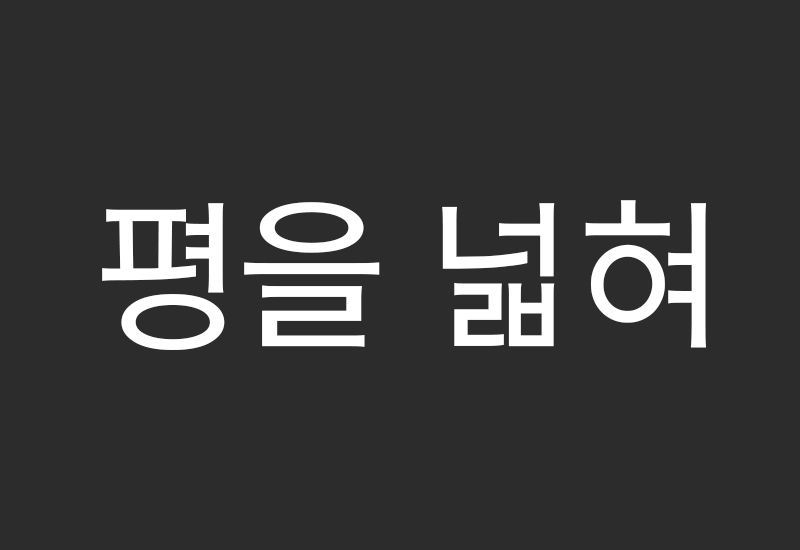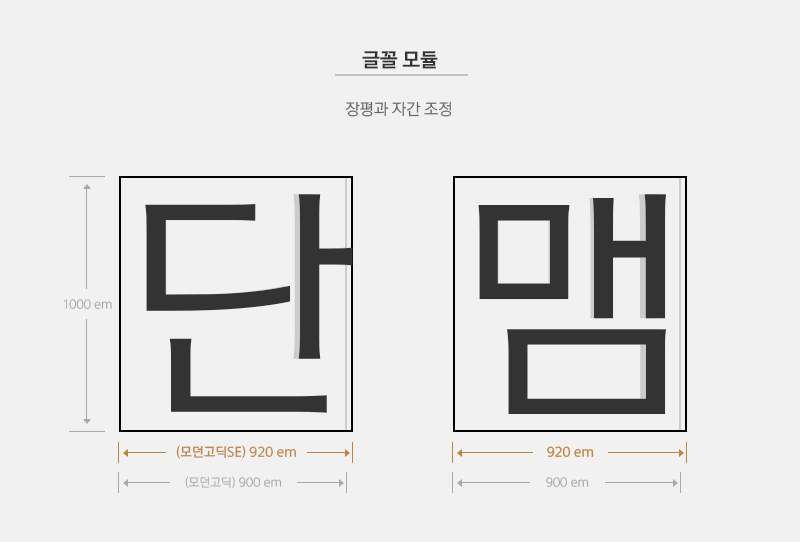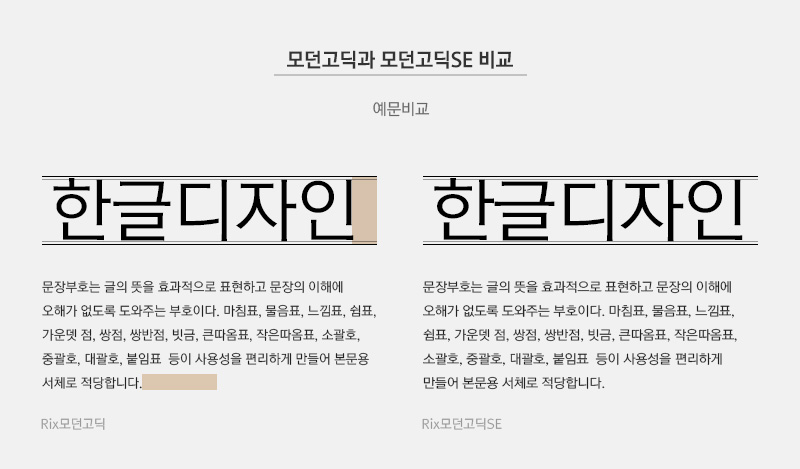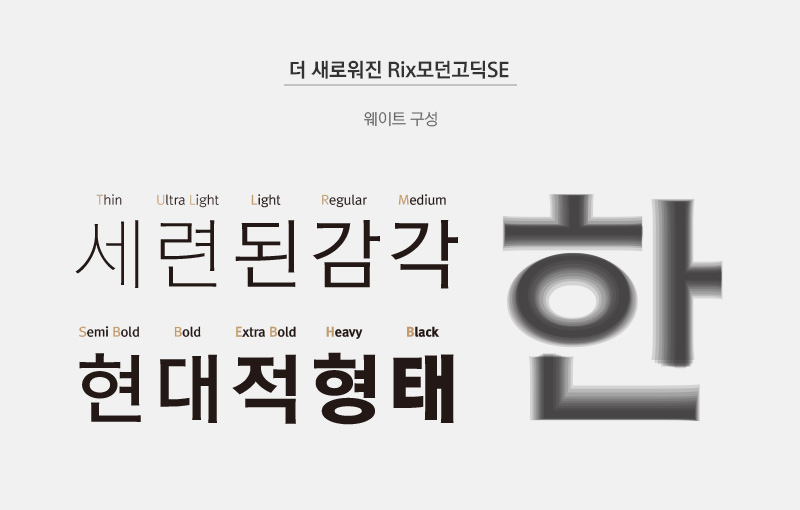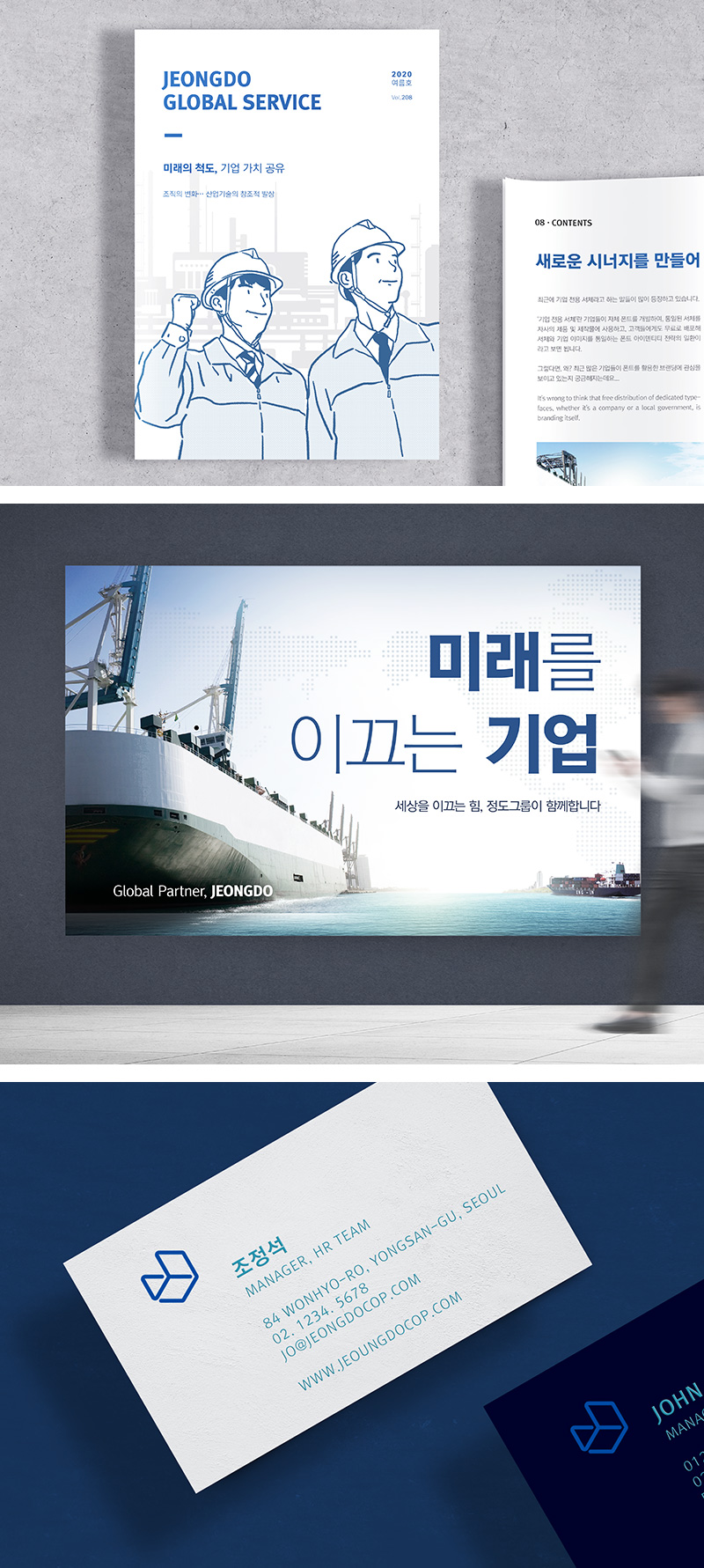
현대적이고 도회적인 본문형의 서체로 적정 자간과 장평의 설정으로 편집자의 수정 없이 최고의 편집 효과를 낼 수 있습니다. 획의 양 끝에 적용된 미세한 세리프로 화면에서 모서리 부분이 뭉개지는 느낌을 없애고 힘 있고 세련된 느낌을 만들어 냅니다.
Rix모던고딕SE
기존의 힘 있고 세련된 느낌에 최신 트렌드를 반영한 평과 자간의 조정으로 편집자의 수정 없이
최고의 편집 효과를 낼 수 있습니다. .
한글, 한자, 영문에 라틴확장으로 유럽언어까지 모두 커버 가능한 Rix모던고딕SE 입니다.
모던고딕과 모던고딕SE 비교
기존 1000*900 모듈에서 고딕SE는 1000*920 모듈로 심미적 안정성을 구현하였습니다.
10가지의 체계적인 웨이트 구성을 갖추고 있고 편안하고 더 완벽해진 본문형 서체입니다.